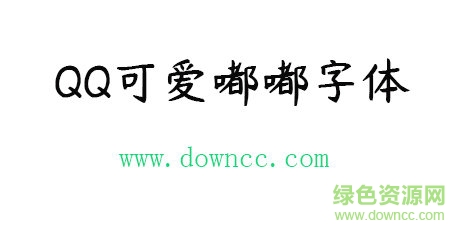
qq可愛嘟嘟字體是一款可愛嘟嘟的qq聊天字體哦,一鍵解壓,安裝即可,使用非常方便,其字體所設(shè)計(jì)的形式非常具有特色,能夠充分展現(xiàn)你可愛的內(nèi)心性格,還是可以分享給別人使用的哦,您還在等什么?喜歡就來下載體驗(yàn)唄!
非常不錯(cuò)的2款qq可愛字體,也叫嘟嘟體,是qq聊天時(shí)常用的兩種qq字體,非常的漂亮,能夠帶給你更好的聊天樂趣。